36 种 Best Western 字体 2023(免费和高级)
无论您是在制作牛仔主题海报、质朴的婚礼请柬,还是只是想为您的设计添加一丝狂野的西部风情,这些字体一定能满足您的需求!
现在,您可能会想,为什么使用西方字体? 西方字体不仅用途广泛,而且具有独特的魅力,可以立即改变任何设计。
它们以其粗犷而大胆的外观唤起了古老西部的精神。 从复古风格的衬线字体到有趣的装饰性脚本字体,每个项目都有一种西方字体。
在本文中,我们将向您介绍 36 种独特的西方字体,它们非常适合为您的设计增添个性和真实性。 这些字体是根据其受欢迎程度、质量和多功能性精心策划的。
无论您是在寻找一种令人尖叫的“狂野西部”字体还是更微妙的选择,我们都能满足您的需求。 因此,准备好探索这些令人惊叹的字体,它们将使您的设计更上一层楼!
最佳优质西方字体
希望为您的设计项目增添一丝狂野西部气息? 别再犹豫了! 我们收集了最好的优质西方字体,它们一定会给您的创作带来一些质朴的魅力。 看看下面的内容,释放你内心的牛仔吧!
西罗马
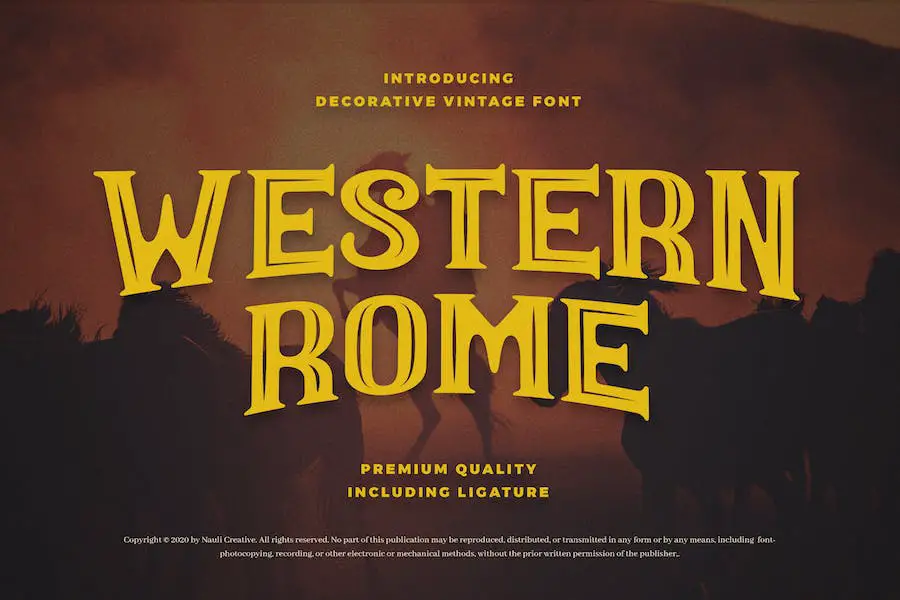
Western Rome 是一种多功能字体,可为您的设计项目增添大胆和复古的气息。 这种字体具有西方风格,非常适合各种场合,例如品牌、邀请函、电影标题等。
无论您想要打造质朴的外观还是增添一丝怀旧气息,西罗马都能满足您的需求。 此外,它易于下载和使用,使其成为图形设计师的便捷选择。
使用西罗马字体为您的项目赋予真实而迷人的西方氛围。
西部黄金
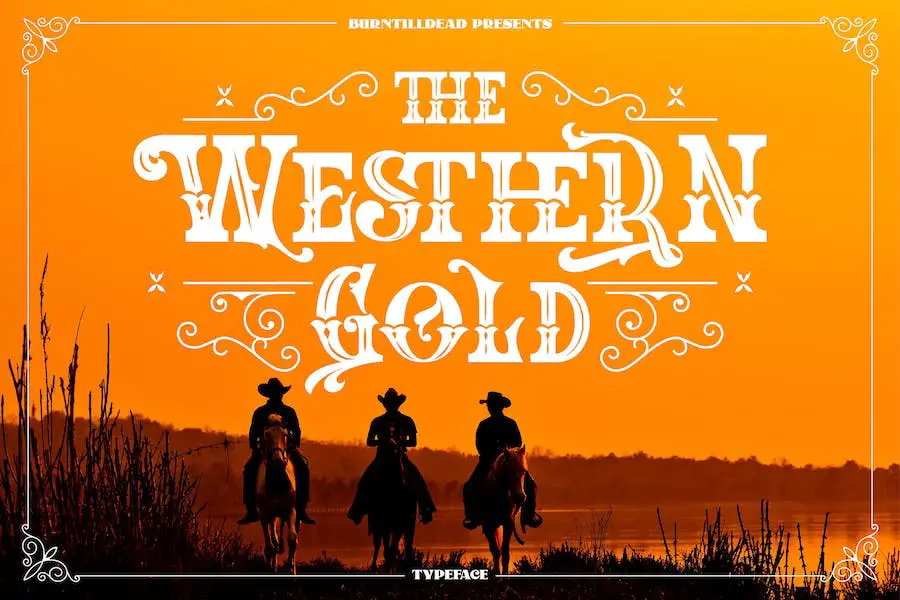
Western Gold是一款全新的西方字体,其灵感来自于经典的美国木标风格。 凭借其替代和连字等 OpenType 功能,该字体非常适合品牌、标题、徽标、贴纸和编辑设计。
它还支持多语言,使其成为使用不同语言的设计师的多功能选择。 你好牛仔,准备好用西部黄金为您的设计增添狂野西部的气息吧!
杜兰戈西部
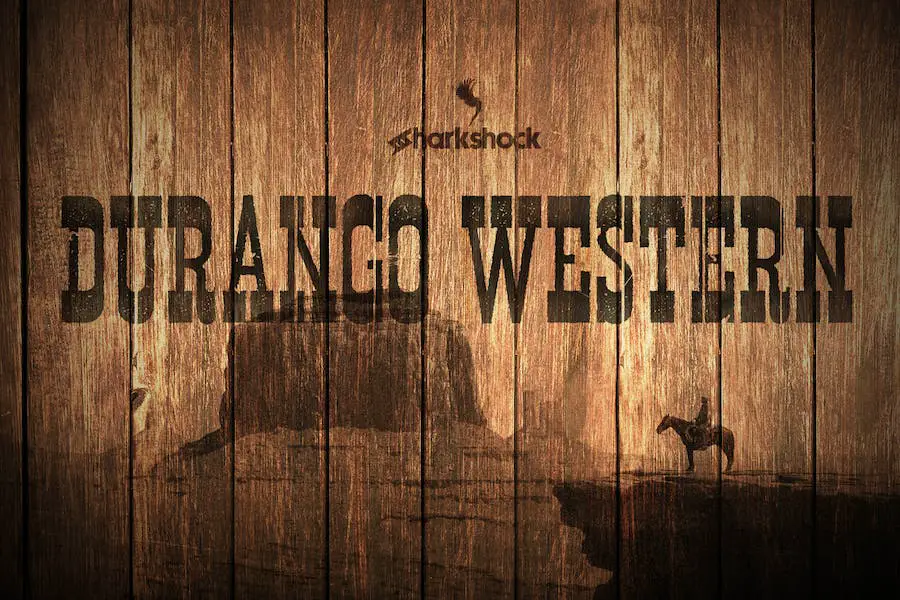
Durango Western 是一种捕捉狂野西部精髓的字体。 凭借其紧密的间距和粗衬线,这种全大写显示字体具有可识别的外观,尖叫着“真实性”。
无论您是设计电影海报、创建社交媒体图形还是设计团队徽标,Durango Western 都是为您的项目赋予西方风格的完美选择。
Durango Western 具有一系列功能,可让您的设计过程更加轻松。 它包括基本和扩展拉丁字符、欧洲口音、标点符号、变音符号、字距调整,甚至俄语的西里尔字符。
死亡西部
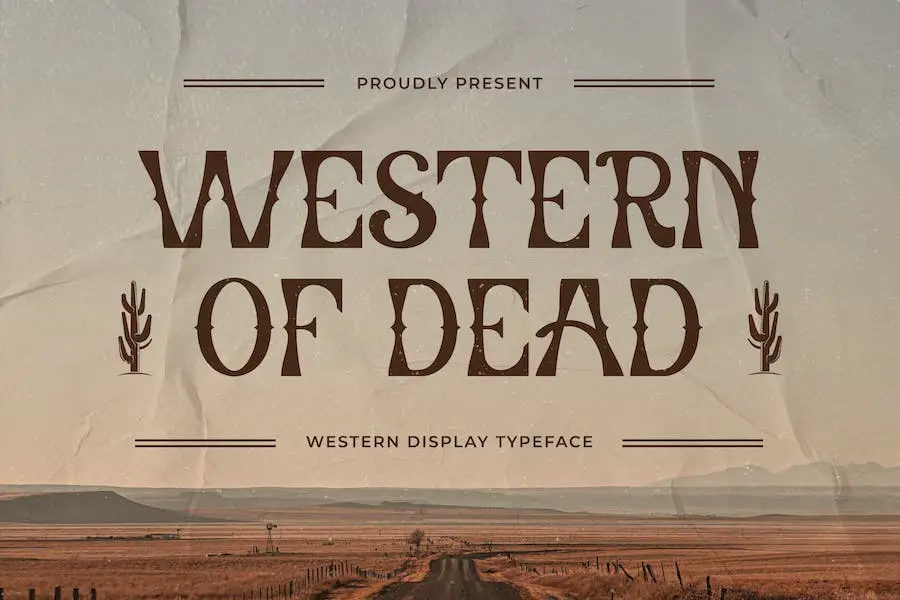
Western of Dead 是一款出色的西方字体,可为任何设计项目增添一抹美感。 无论您是想要复古还是垃圾风格、创建儿童游戏、设计引言或标题、品牌、书籍封面或海报,这种字体都是完美的选择。
它用途广泛,可以增强任何需要西方审美的创作。 借助《Western of Dead》,您的设计将脱颖而出并吸引观众。
西部兄弟
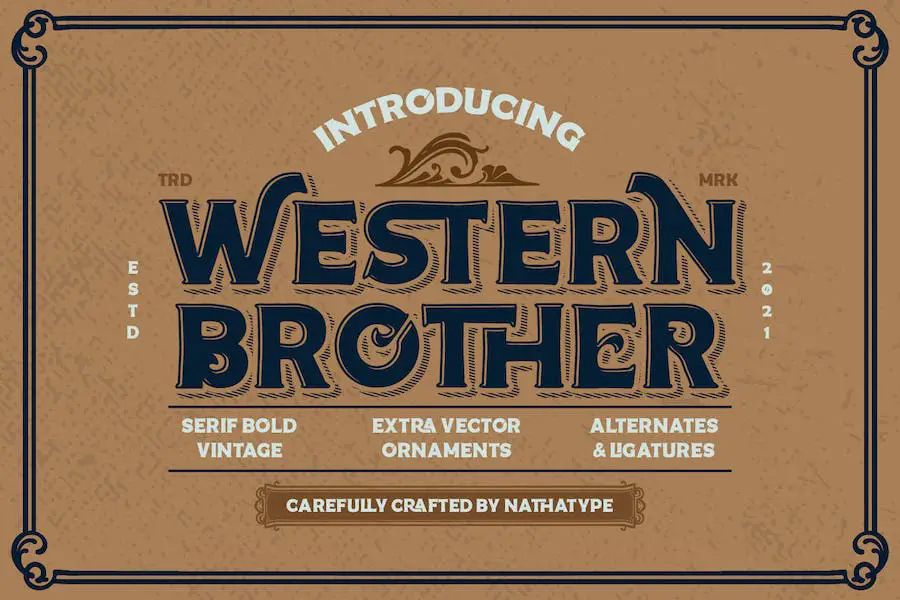
Western Brother 是您一直在等待的字体,可将您的品牌提升到一个新的水平。 凭借其复古风格和艺术风格,这种大写字体为任何项目或促销活动增添了独特而有趣的元素。
无论您需要令人惊叹的徽标、引人注目的书籍封面、引人注目的海报、时尚 T 恤设计还是引人入胜的广告,这款一体化包装都能满足您的需求。
Western Brother 的突出特点之一是它的额外装饰、连字和风格设置,提供更多的设计选项和定制。 通过这些添加的元素,您可以真正使您的创作脱颖而出。
西尔瓦诺·韦斯特
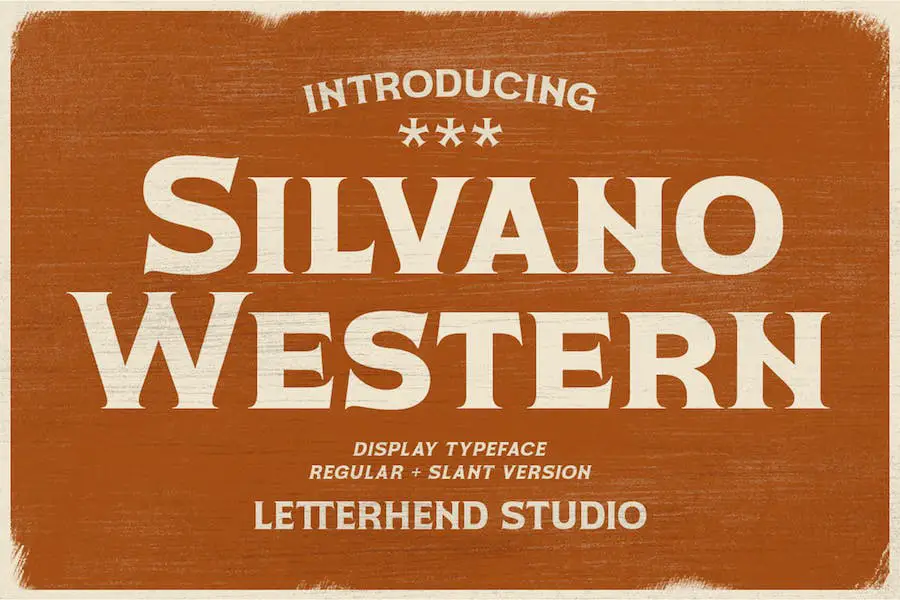
Silvano Western 是一种显示字体,可为您的设计项目增添经典的西方风格,无论是徽标、邀请函、标签、杂志、书籍还是贺卡。 它也非常适合时尚、包装、化妆品、文具、小说和任何类型的广告目的。
借助 Silvano Western,您将可以使用各种字形变体,使您的设计真正独一无二。 此外,它还提供常规版和倾斜版,让您创造出不同的风格。 该字体也是多语言的,因此您可以将其用于不同语言的项目。
韦斯托夫
Westof 是一种强大的衬线西方字体,结合了锐利和圆润的边缘,打造出大胆而时尚的外观。 它非常适合在您的设计项目中创建强大而有影响力的标题。 凭借其装饰性的西式形状,您将拥有更多创意选择。
西部复古
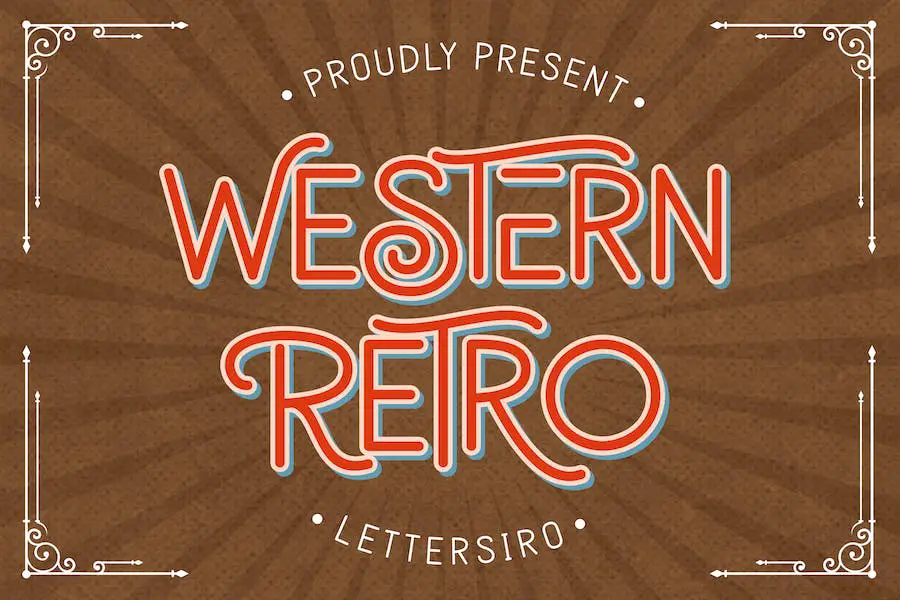
Western Retro 是一种充满活力且纤细的无字体,可为任何设计带来怀旧气息。 其复古的感觉一定会引起人们的注意。 该字体包含替代字体,使其更适合您的项目。
埃斯特班
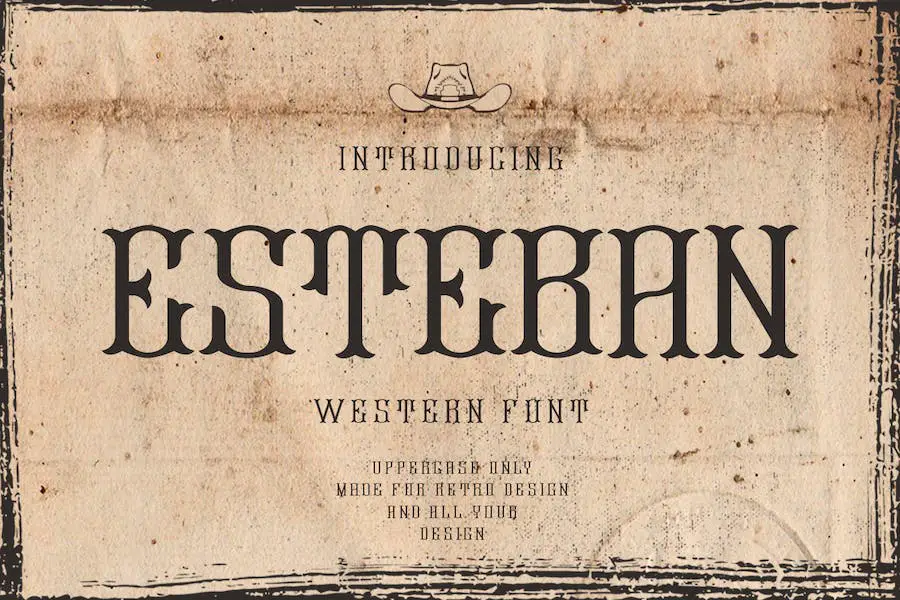
对于寻找古老的西方字体来增强其设计项目的图形设计师来说,Esteban 是一个绝佳的选择。 该字体拥有时尚而现代的无衬线风格,非常适合海报、网页设计、品牌、插图、徽章等。
休斯顿
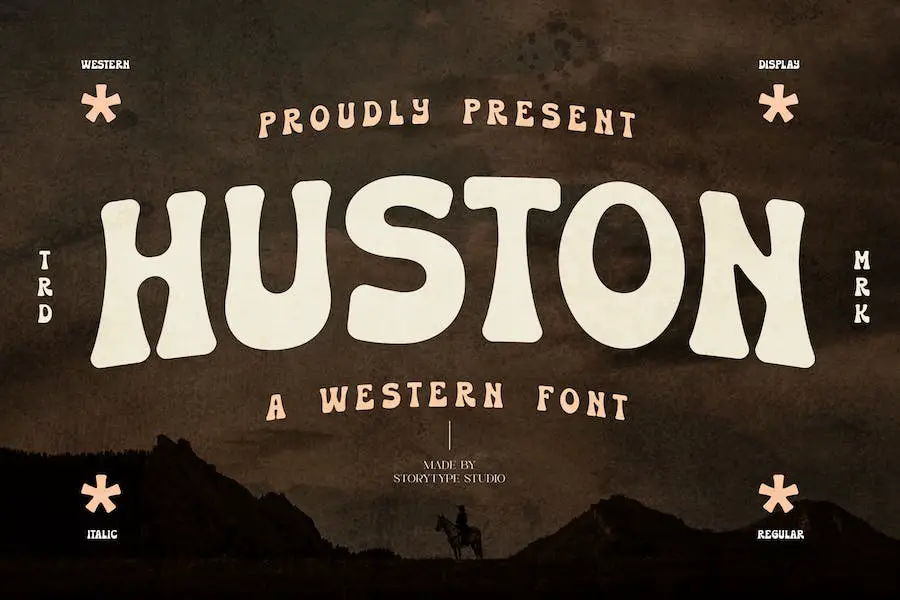
Huston 是一种现代西方字体,可以提升您的数字和印刷创意项目的设计。 它是海报、社交媒体帖子、品牌和个人项目的理想选择。
凭借其时尚的设计,该字体一定会吸引观众的注意力并增强您作品的整体美感。 立即尝试 Huston,看看它如何将您的设计提升到新的水平。
光迹
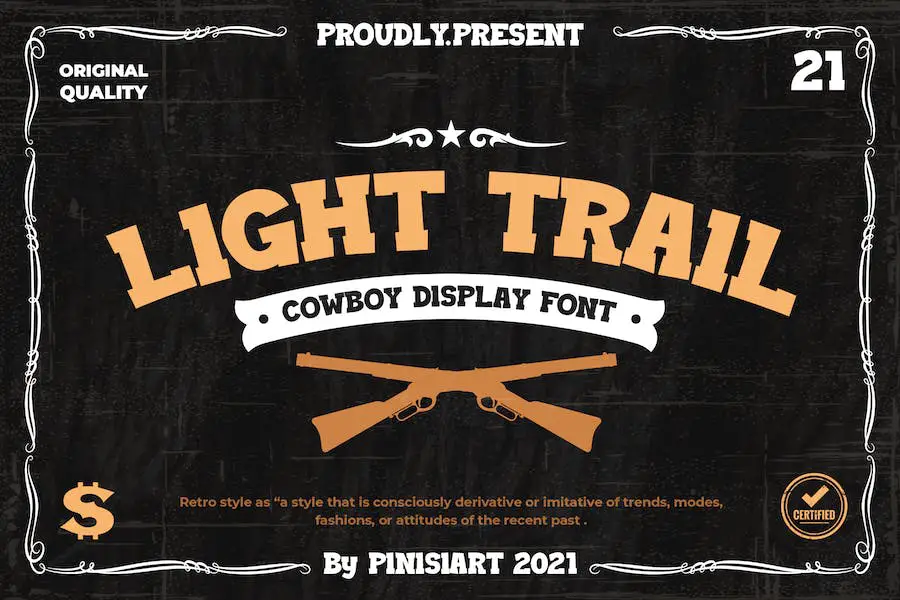
Light Trail 是一种友好的粗体衬线字体,捕捉了牛仔柔软的一面。 凭借其流畅和平易近人的美感,该字体非常适合增强具有西方主题的项目。
无论您是设计书籍封面、在线游戏、文具、徽章式徽标、海报、生日邀请函、YouTube 封面、缩略图还是社交媒体页面封面,Light Trail 都会为您的作品增添一抹狂野西部的魅力。
车轴润滑脂
Axle Grease Display Font 是一种复古的西方字体,可为您的设计增添独特的触感。 这种字体的突出特点是每个字母上的装饰元素,给您的项目带来真实和经典的感觉。
无论您是在设计徽标、版式设计、杂志标题还是书籍封面,这种字体都会提升整体外观。 它还非常适合网站文本标题、产品包装名称、T 恤刻字等。
纳吉塔
'隆重推出 Nagheta,这是一种美丽而优雅的西方字体,非常适合增强您的徽标设计、杂志布局、社交媒体帖子、宣传册设计等。 凭借其复古风格,Nagheta 为任何项目增添了一抹旧世界的魅力。
这种西方字体具有多种功能,可以满足您的设计需求。 它包含数字,让您可以为您的设计添加时尚且引人注目的数字。 包含标点符号可确保您可以正确地为文本添加标点符号,以保证清晰性和专业性。
Nagheta 中的大写字母具有大胆而有影响力的外观,非常适合标题和标题。 此外,小写字母为您的设计增添了一丝精致和多功能性。
莫加特
Mogathe 是一种板衬线字体,可为您的设计项目带来复古的西方外观和感觉。 受西方生活时代的启发,它提供了四种变体:常规、邮票、马刺和马刺邮票。
这种字体具有精心制作的风格,非常适合需要旧西部风格的品牌和包装。 它还包括用于增加多功能性的替代方案。 无论您需要添加怀旧氛围还是创建乡村风格的设计,Mogathe 都是理想的字体选择。
另外,它支持多种语言并附带所有必要的标点符号。 利用这种西方字体的魅力和特色来提升您的设计。
西方坚毅
Western Grit 是一款手绘字体,外观仿旧且充满个性。 它体现了旧式通缉海报和西方标志的粗犷感觉。
该字体 100% 手工制作,包含多种字符,包括中欧和西欧字符、数字、标点符号和符号。
Western Grit 共有 323 个字形,对于希望为其项目添加真实而独特风格的图形设计师来说是完美的选择。
无论您是设计复古风格的海报还是创建引人注目的徽标,这种字体一定会将您的设计提升到一个新的水平。 今天就用 Western Grit 为您的项目增添一丝勇气和个性。
性急
Hothead 是一种出色的大小写衬线字体,从丰富而充满活力的美国西部文化中汲取灵感。 它完美地结合了传统和现代元素,给您的设计带来一丝复古的西方魅力。
该字体共有 258 个字形和广泛的拉丁脚本语言支持,包括从 A 到 Z 的字符、数字和标点符号,提供了无限的设计可能性。
无论您是要创建大胆的徽标、引人注目的标题、醒目的海报还是出色的包装设计,Hothead 都是让您的项目大放异彩的终极工具。
韦斯特伍德
Westwood 是一种独特而时尚的显示字体,可为您的项目增添一丝西方魅力。 凭借其复古/复古美学,它非常适合创造脱颖而出的设计。
该字体有八种不同的变体,包括常规、垃圾、内联、内联垃圾、粗体、粗体垃圾、阴影和阴影垃圾,为您提供了大量的选择。
常规和垃圾选项提供干净或做旧的外观,而内联和内联垃圾变体则增加了额外的细节水平。
如果你想让你的文字做出更大胆的陈述,粗体和大胆的垃圾风格是一个很好的选择。 为了增加深度,阴影和阴影垃圾选项可创建微妙的阴影效果。
波尔托桑斯
POERTOSANS 是一款复古西方字体,以其大、粗体、破骨的风格带回干燥、尘土飞扬的西方世界。 这种字体非常适合您所有的西方主题项目,从书籍和在线游戏到海报和邀请函。
它完全可以访问,无需任何额外的设计软件,并且包含基本的拉丁字符、数字和标点符号。
无论您是图形设计师还是 DIY 爱好者,您都可以在 Adobe Illustrator、Adobe Photoshop、Adobe InDesign 甚至 Microsoft Word 中轻松使用 POERTOSANS。 因此,开始设计并与 POERTOSANS 一起在您的项目中展现狂野的西部吧!
范戴克
Van Dyke 是一种强大的西方字体,可为您的设计项目带来狂野西部的粗犷魅力。 这种字体是游戏规则的改变者,非常适合希望增添冒险和兴奋感的图形设计师。
结论
总之,我们探索了西方字体的世界以及它们如何极大地增强您的图形设计项目。
从衬线字体的经典和大胆的美学到手写字体的质朴魅力,每种类型都为您的设计带来了自己独特的风格。
通过将西方字体融入您的作品中,您可以创造引人注目且引人入胜的视觉效果,给人留下持久的印象。